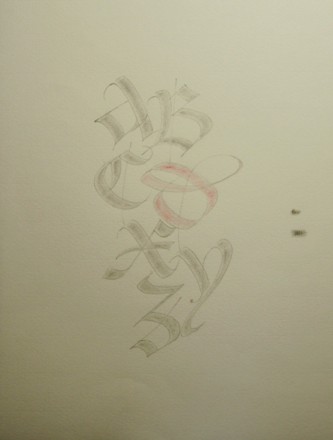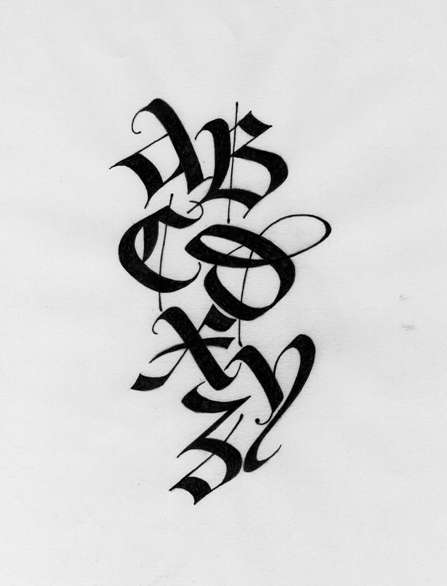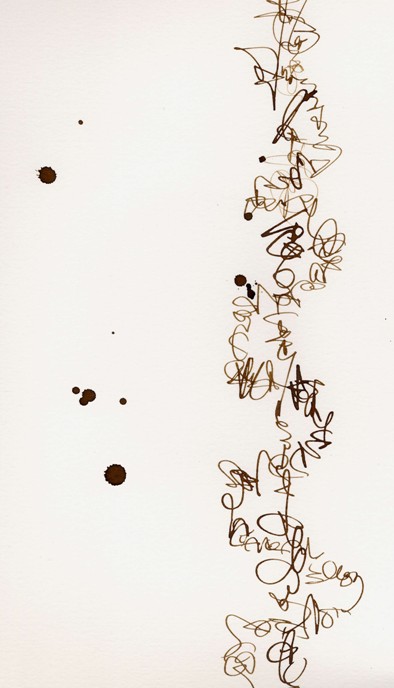
ダブルペンシルが…
以前、削る君で芯をとんがらかしたダブルペンシルで書いた
アルファベットです。そのまんまでほっとかれてました…・
先日、Kさんから「樹脂版の印刷を試すから何か原稿ありますか?」
と聞かれたので、ゴソゴソ探してきました。
しかし、あまりにうす〜いので、コピーしてもほとんどうつりません。
仕方ないので、少し中を濃くしてみたのです。
本当は、鉛筆のうすい色使いで塗ってあるほうが好みなんですが、
原稿にならないのでは仕方なし…。
我が家からコピー機のあるコンビニまでいちいち出かけるわけに
もいかず、こういう時はスキャンします。サイズがA4だったので
問題ありませんでした。
それでも不安になったので、
一度印刷してその紙を更に
今度はピグマで塗りこんでみました。
だいたい樹脂版印刷もどんなものか
わからないのに…原稿に手をつけて
しまいました…。
でも一度スキャンしてみると、この先
いろんな所に使えます。
私は特に紙マニアなので、いろいろ刷って質感を試してみたいです。
こんな「へんてこ線」(実際、ファイル名は同じです)もスキャン
しておけば、カードなどで、ポイントに使えます。
これは捨てるのにはちと惜しい…と思われたら、とにかく
スキャンしておくのも手です。
こうやってあれこれ遊んでいるのは作品作りから離れて
気分転換によいです。